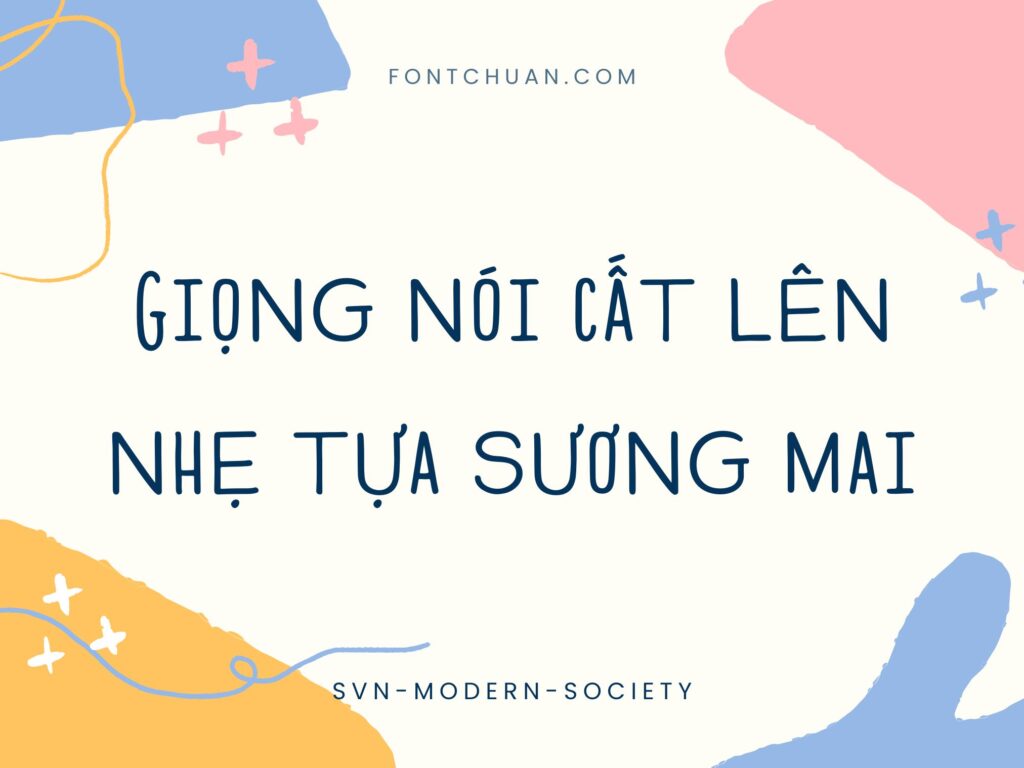
Font SVN Modern Society Việt Hóa
Tác giả Font: Ayca Atalay
Font SVN Modern Society là phiên bản Việt hóa của kiểu chữ Modern Society, được thực hiện bởi STYLEno.1 Fonts. Đây là một kiểu chữ viết tay hiện đại với toàn bộ ký tự được thể hiện bằng chữ in hoa, mang đến phong cách cá tính và nổi bật. Dù mang hơi hướng tự do của chữ viết tay, nhưng Modern Society vẫn giữ được cấu trúc rõ ràng, giúp dễ đọc và dễ ứng dụng. Font bao gồm đầy đủ chữ hoa, chữ thường, chữ số và dấu câu, đồng thời hỗ trợ đa ngôn ngữ. Với đường nét dày dặn và bố cục chắc chắn, font rất thích hợp cho các thiết kế mạnh mẽ và phá cách như logo, poster, nhãn hàng hoặc nội dung truyền thông kỹ thuật số.
SVN Modern Society phù hợp với các dự án thiết kế cần tạo điểm nhấn cá tính như tiêu đề tạp chí, bao bì mỹ phẩm, video truyền thông và bảng quảng cáo. Các ngành nghề như quảng cáo, công nghệ và giáo dục có thể tận dụng hiệu quả kiểu chữ này. Ngoài ra, font cũng thích hợp sử dụng trong các dịp đặc biệt như Tết, Giáng sinh, Valentine và các lễ hội sáng tạo khác.